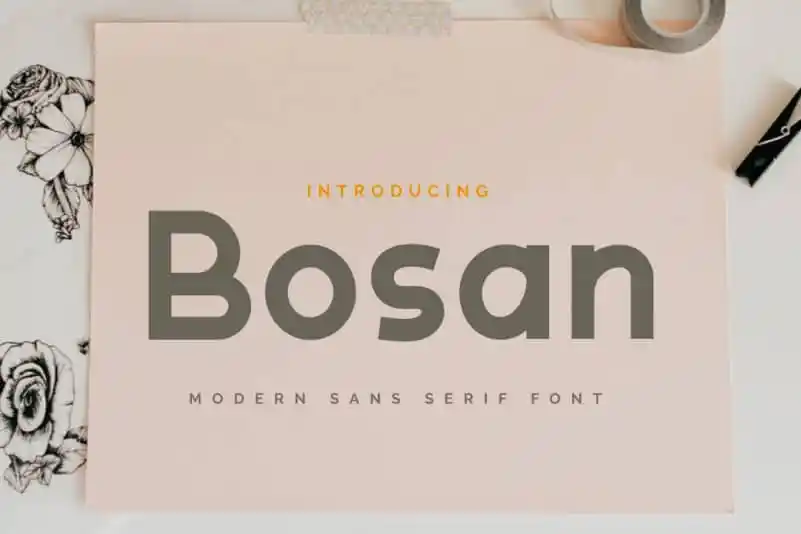
Bosan Sans Serif Font – Download Grátis
A Bosan Sans Serif é uma nova tipografia sans serif que transmite alegria e elegância ao ser usada tanto para título quanto para parágrafos. É ideal para comunicar mensagens de forma confortável e envolvente, seja ela um texto longo ou um grito de encorajamento em grandes letras. A Bosan Sans Serif é perfeita para criar ambientes de design que buscam transmitir uma atmosfera leve e descontraída, sem perder a elegância. Ela é versátil o suficiente para ser usada tanto nas cabeçalhos quanto nos parágrafos, tornando-a ideal para qualquer tipo de mídia visual em seu site ou aplicativo. Compreender e usar esta fonte pode transformar sua comunicação no ambiente digital do seu negócio, fazendo a diferença entre uma mensagem profissional e um design que transmite alegria e conforto àqueles que recebem sua mensagem.